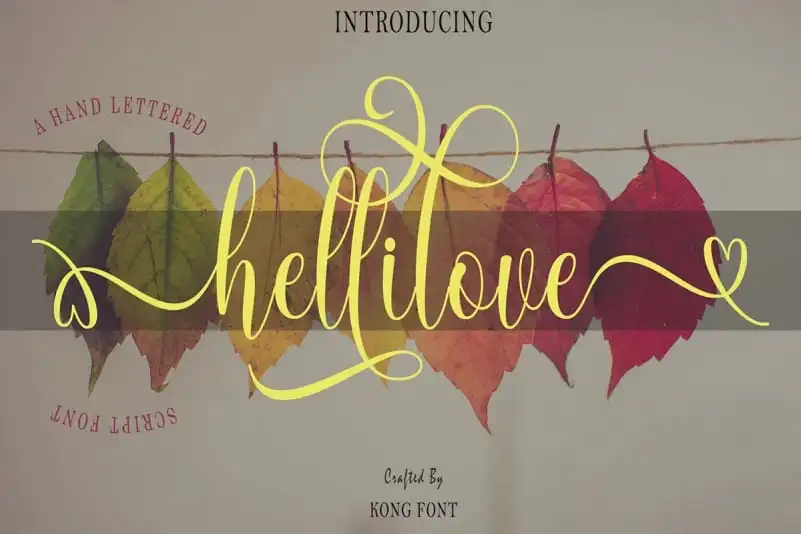
Hellilove Calligraphy Font – Fonte Grátis
Hellilove Calligraphy Font
Hellilove Calligraphy Font é uma elegante e eterna fonte escrita a mão que adicionará vida ao seu design. Seu caráter tem um brilho encantador, dando à sua peça de trabalho um ar único. Além disso, oferece uma gama completa de alternativas em maiúsculas para dar aos seus letras aquele visual cuidadosamente personalizado do texto escrito a mão. Também inclui acentos finais e iniciais em minúsculas que se curvam suavemente. Hellilove é ideal para criar logotipos memoráveis, estilos de marca distintivos e citações intrigantes. Cada letra traz um toque único e bonito, garantindo que sua criação seja imortalizada ao vivo no mundo digital. Perfecto para designers a procura de uma fonte escrita a mão que dê vida à sua ideia de design.